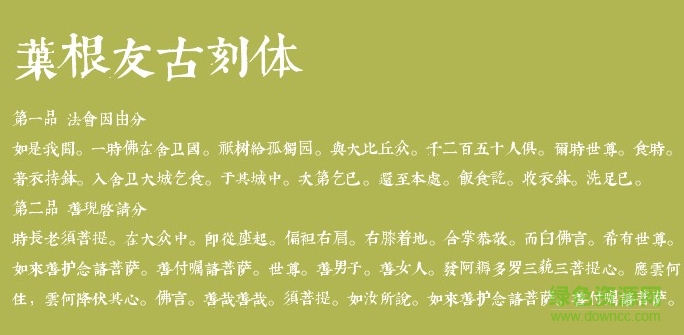
葉根友古刻體是一款非常好看的書法字體,古香古色風(fēng)格的字體,特別適合海報設(shè)計,喜歡的可以下載看一下,小編提示該字體是收費(fèi)的。
葉根友古刻體是一款具有古意的書法字體,整個字形融合了這個書法的一種古體韻味,點(diǎn)橫與捺都在書寫著不同漢字的傳奇色彩,是特別具有中國風(fēng)的書法字體。葉根友古刻體,一種返璞歸真的腳步在世間凝固,反過頭去看看以前的字體,感覺是美好的,也是戀舊的一種情結(jié),這款字體就是利用傳統(tǒng)與現(xiàn)代的筆形結(jié)構(gòu)進(jìn)行設(shè)計的古刻字體,風(fēng)格優(yōu)雅而不失古風(fēng)藝術(shù)。